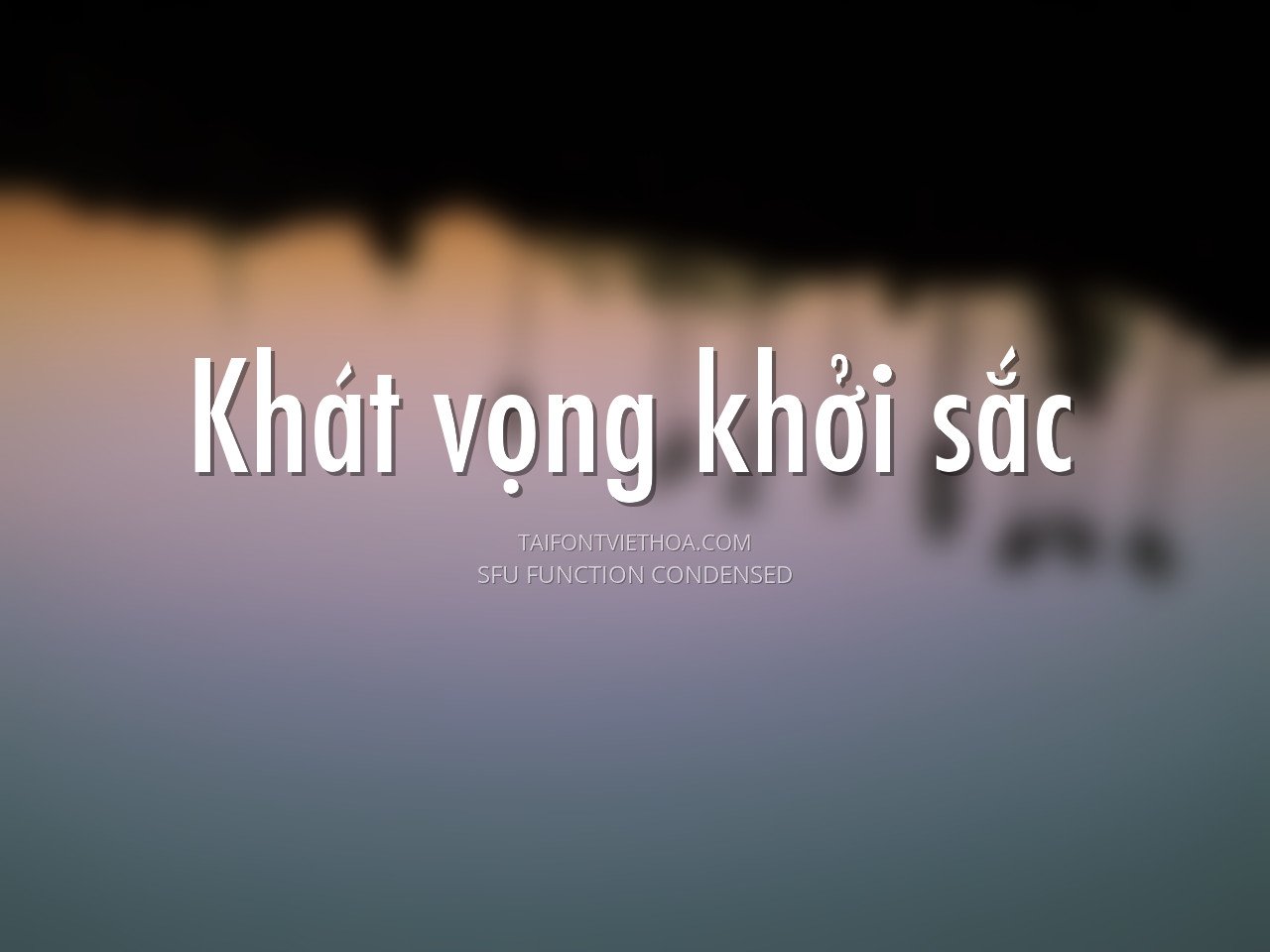
Giới thiệu về font SFU Function – Phong cách sans-serif hiện đại, hiệu quả cho thiết kế số
SFU Function là phiên bản Việt hóa của một kiểu chữ sans-serif hiện đại mang đậm tính hệ thống và kỹ thuật. Font được thiết kế với triết lý “hình thức phục vụ chức năng” – đúng như cái tên “Function”, nhằm mang lại khả năng trình bày rõ ràng, tối ưu khả năng đọc và sự ổn định trong mọi kích thước hiển thị. Đây là kiểu font cực kỳ phù hợp với thời đại số, nơi mà sự tối giản và rõ ràng luôn là ưu tiên hàng đầu trong thiết kế.
Phiên bản SFU Function được Việt hóa đầy đủ, hỗ trợ dấu tiếng Việt và bộ ký tự mở rộng đa ngôn ngữ, tạo điều kiện thuận lợi cho nhà thiết kế khi cần triển khai các dự án đa nền tảng. Taifontviethoa.comđã lựa chọn font này trong bộ sưu tập font công nghệ hiện đại, phục vụ các nhu cầu thực tế như giao diện số, thương hiệu số và truyền thông kỹ thuật số.
Thiết kế tối giản, hệ thống hóa và ứng dụng mạnh mẽ của SFU Function
SFU Function có kết cấu sans-serif chuẩn hình học, các ký tự đồng đều về độ rộng và chiều cao, mang lại cảm giác chắc chắn và hệ thống. Font không có chi tiết trang trí thừa, giúp tăng khả năng đọc ở cả kích thước nhỏ và môi trường hiển thị số. Khoảng cách giữa các chữ được tính toán hợp lý, tạo nên sự liền mạch và nhất quán trong bố cục.
Ứng dụng lý tưởng: thiết kế website, giao diện người dùng (UI), app di động, tài liệu nội bộ, nhận diện thương hiệu công nghệ, infographics, bảng dữ liệu, và bản trình bày chuyên nghiệp. Ngành nghề phù hợp: công nghệ thông tin, tài chính số, kỹ thuật, giáo dục trực tuyến, khởi nghiệp, thương mại điện tử và các lĩnh vực cần sự tối giản, chính xác và hiện đại trong thiết kế.